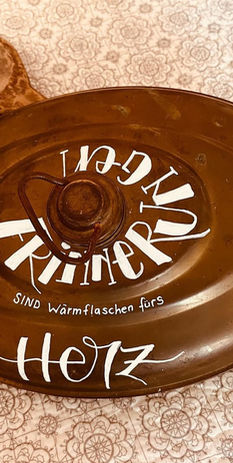
Zum ersten Mal darf ich Teil des Schriftart-Festivals sein, und ich freue mich sehr, meine Arbeiten sowohl auf dem ArtMarkt als auch im Rahmen der Ausstellung präsentieren zu dürfen.
Meine Liebe zur Kalligrafie begann 2009 mit dem ehrgeizigen Plan, die komplette Papeterie für meine eigene Hochzeit selbst zu gestalten. Rückblickend frage ich mich manchmal, wie ich das damals guten Gewissens verschicken konnte - aber genau dort nahm meine Begeisterung für schöne Schrift ihren Anfang. Nach einigen Umwegen habe ich in der Spitzfederkalligrafie meine Heimat gefunden, und sie hat mich bis heute fest im Griff.
Unter meinem Label "à la hand - Glück, Stoff und Tinte" verbinde ich klassische und moderne Schrift mit einem Gespür für Material, Haptik und gelebte Oberflächen. Besonders alte Holzobjekte faszinieren mich, weil sie Geschichten in sich tragen und mit meiner Schrift darf eine weitere hinzukommen. Meine Arbeiten dürfen berührt werden - im Herzen ebenso wie mit der Hand. Seit 2019 bin ich selbstständig, begleite Hochzeitspaare mit der passender Papeterie, darf gleichermaßen für Privatpersonen, Firmen und Behörden im Bereich Kalligrafie und Gravur tätig sein, gebe meine Leidenschaft in Workshops weiter und liebe es auf Kunsthandwerkermärkten meine Arbeiten zu präsentieren.
Ich freue mich auf Begegnungen, regen Austausch, viele neugierige Blicke und das stille Innehalten vor der Schrift.